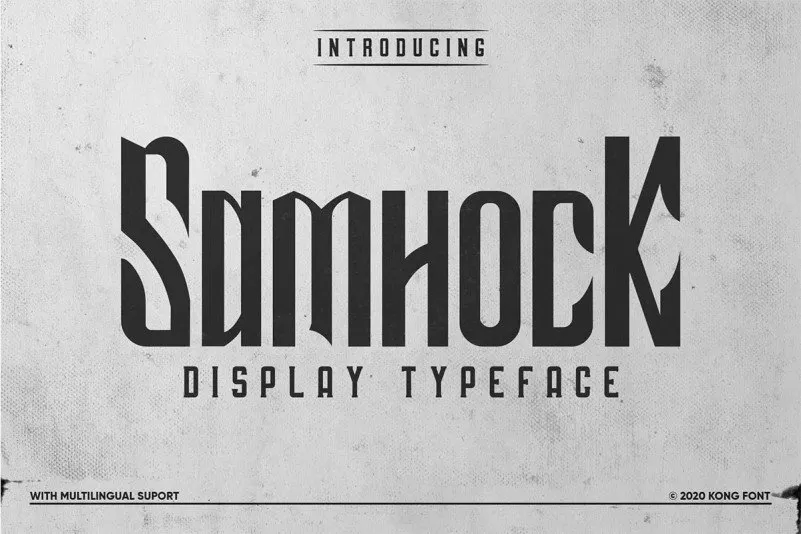
Samhock Display Font – Download Grátis
Introduzimos Samhock Display Font, uma tipografia de exibição inovadora e interessante. Perfeita para aplicações em headlines que precisam destacar-se entre os demais, esta fonte também se destaca em diversas formas formais. Ideal para branding, embalagens, logos, jogos de design, headlines e moda, Samhock é moderna e rústica ao mesmo tempo. Combinando perfeitamente com uma tipografia sans-serif minimalista, ela oferece flexibilidade para diferentes ambientes de uso. Este tipo de fonte é particularmente atraente quando aplicada em projetos visuais que exigem um toque de originalidade e destaque. Seja em uma campanha publicitária ou em um projeto de design gráfico de moda, Samhock Display Font certamente se encaixa perfeitamente, transformando qualquer layout no seu site ou produto impresso.